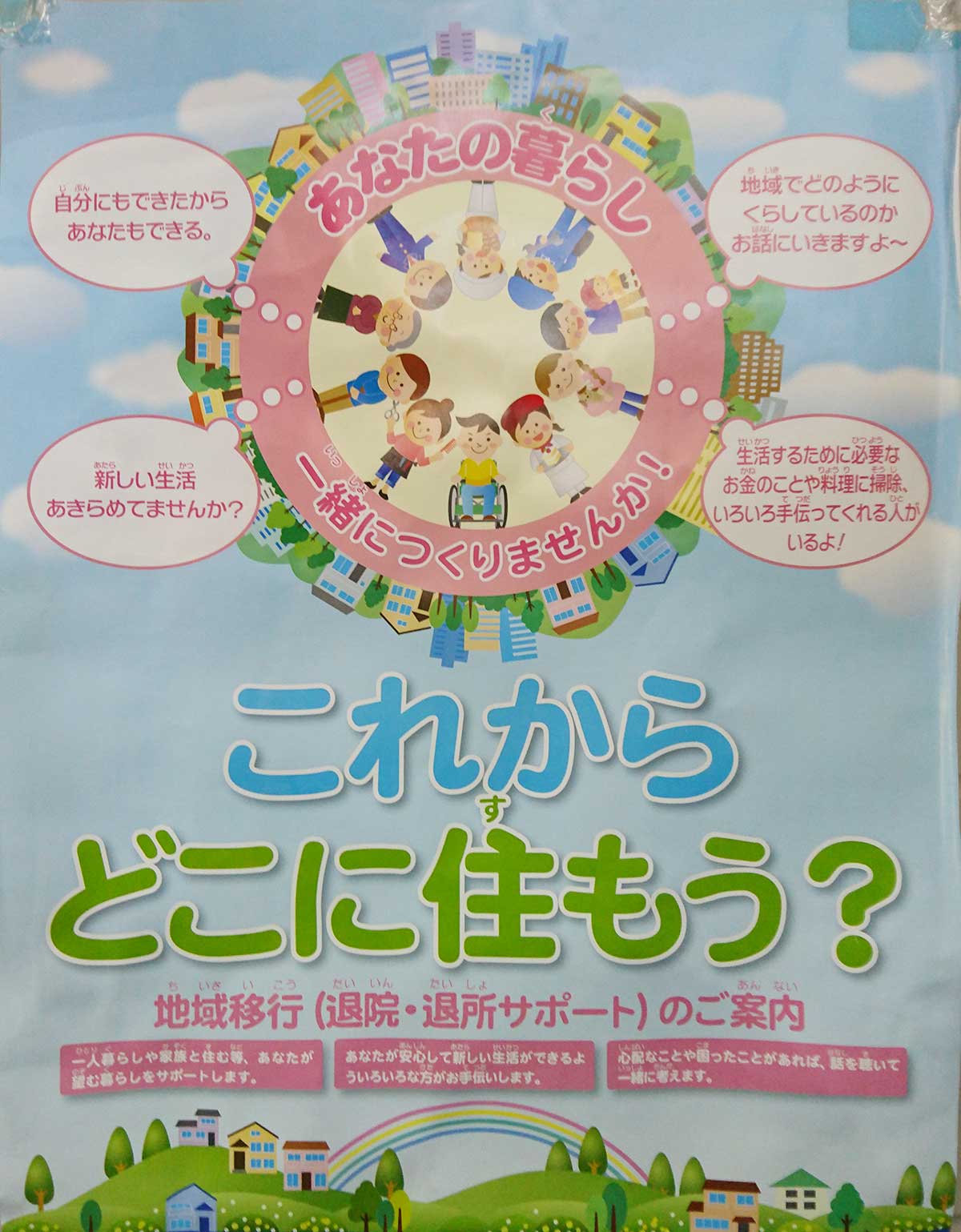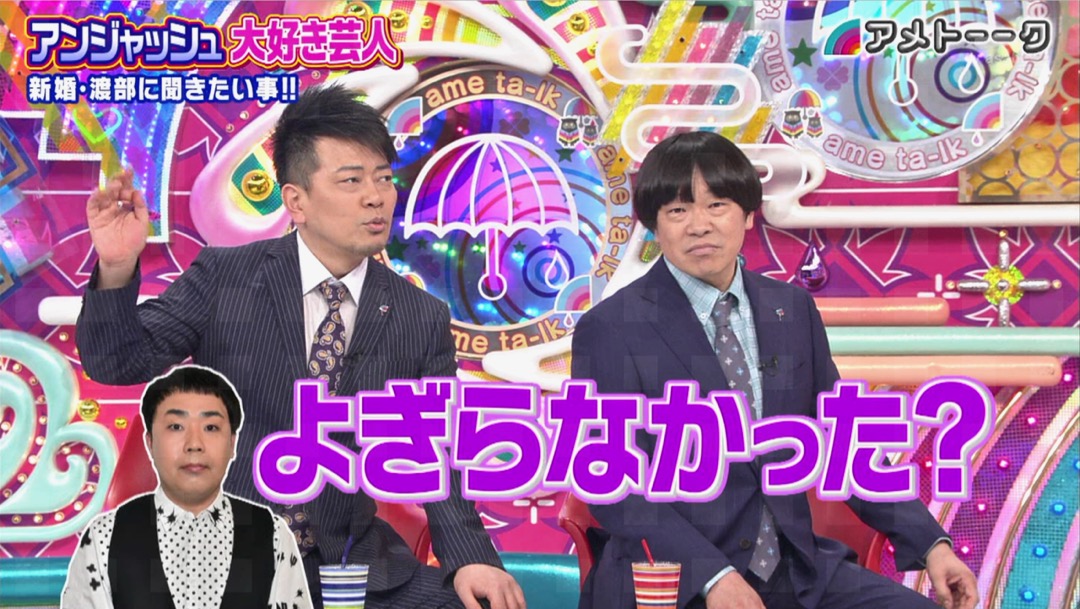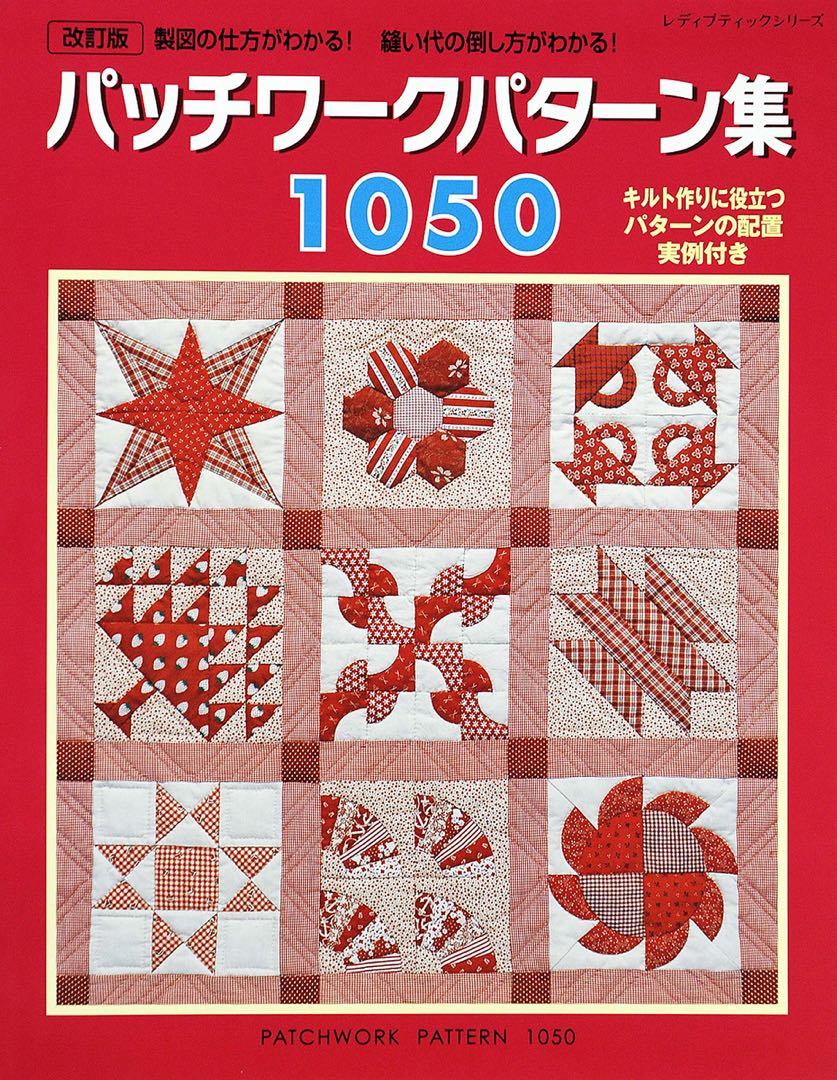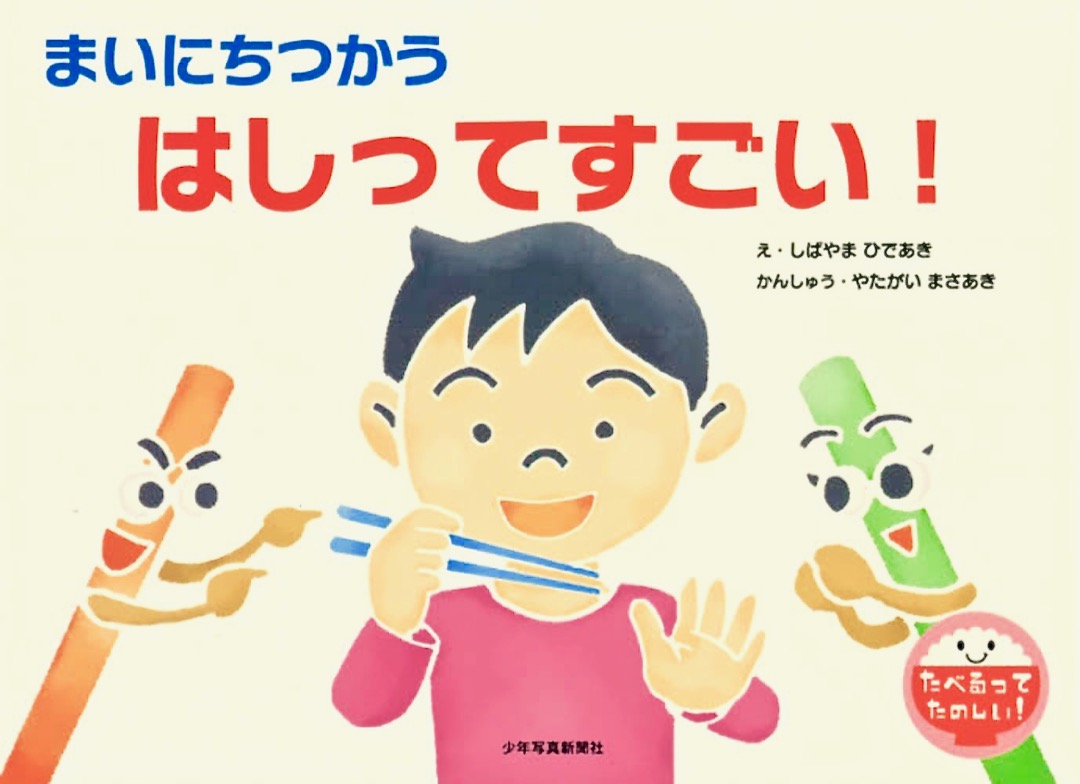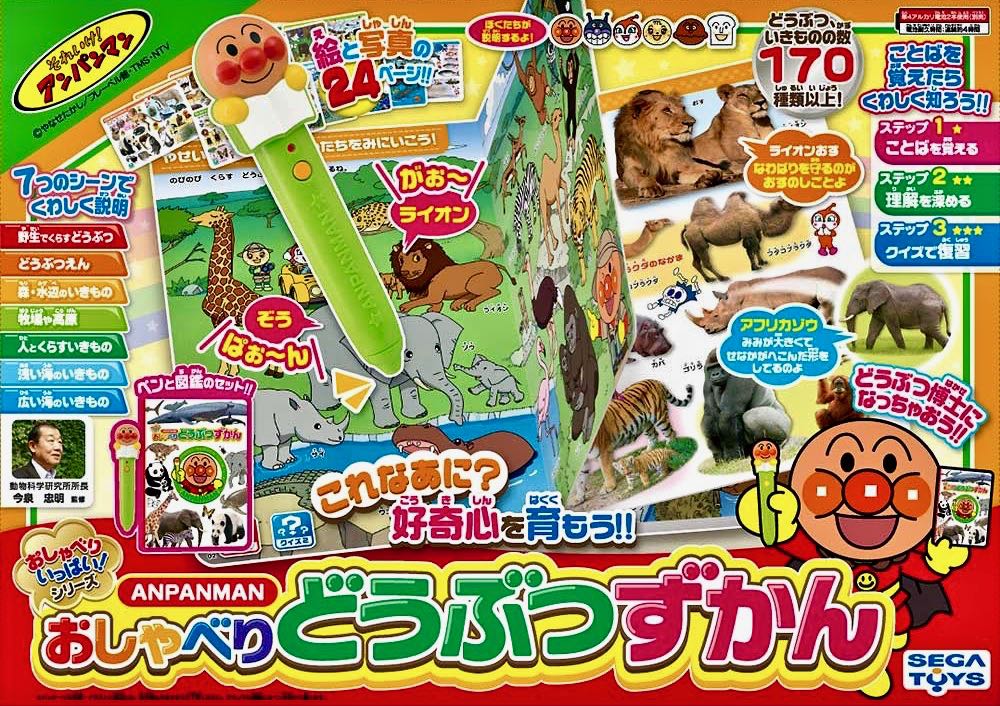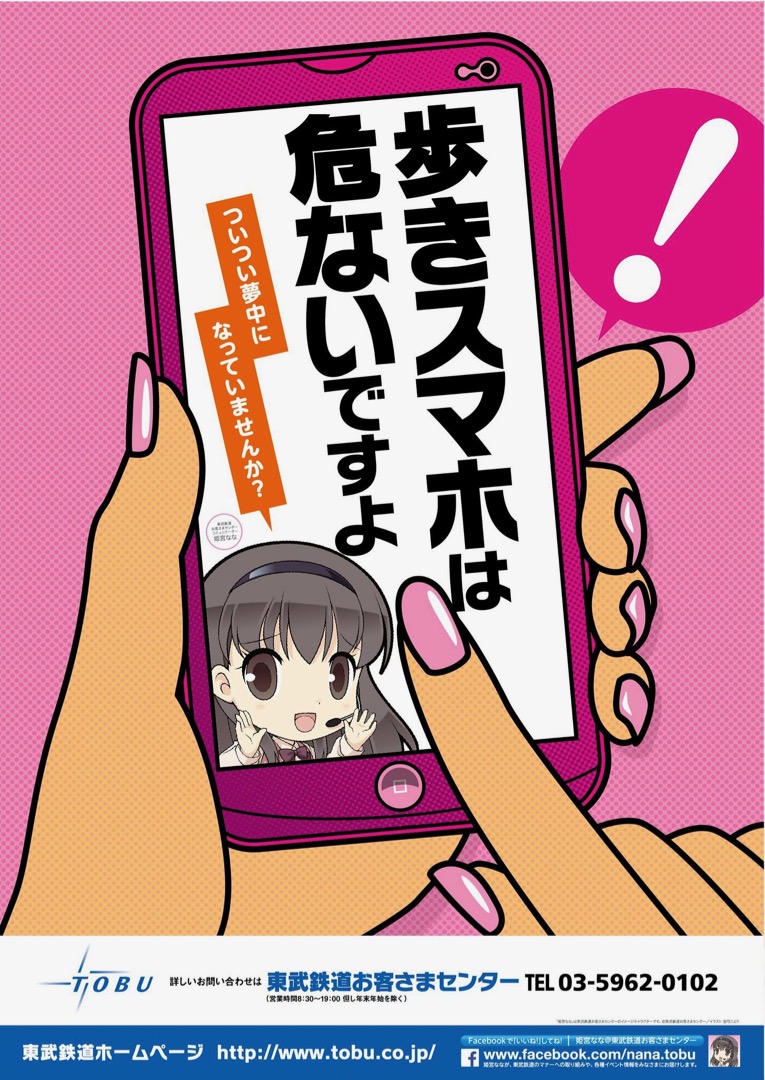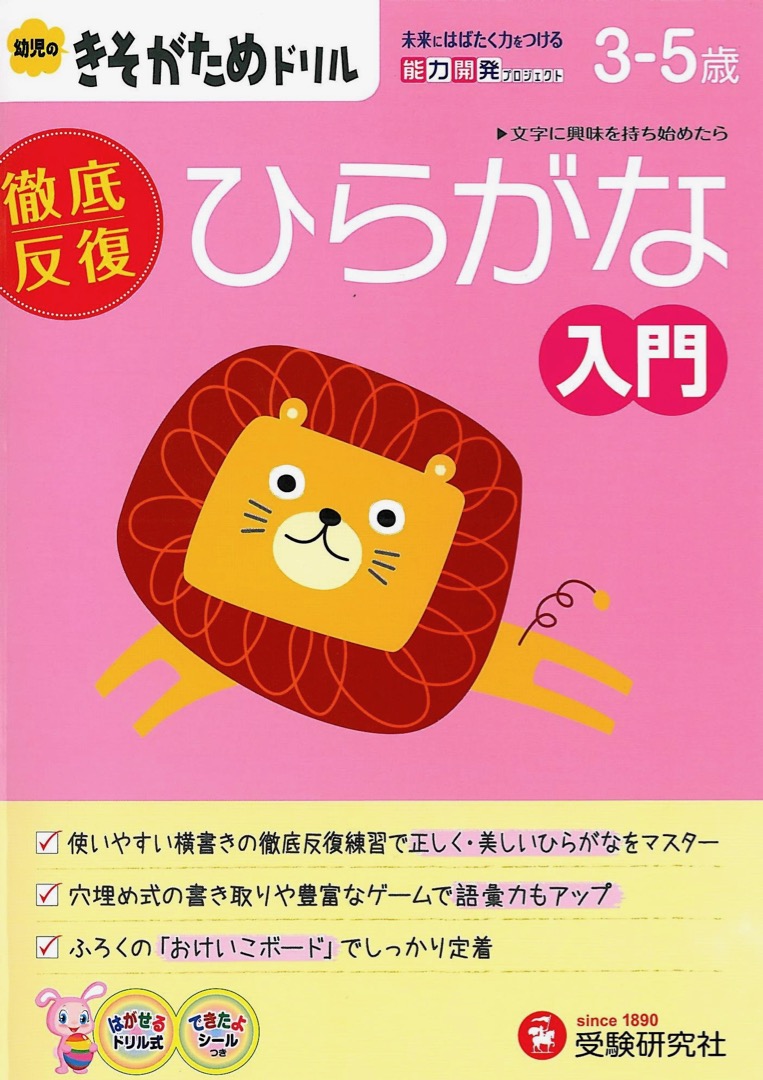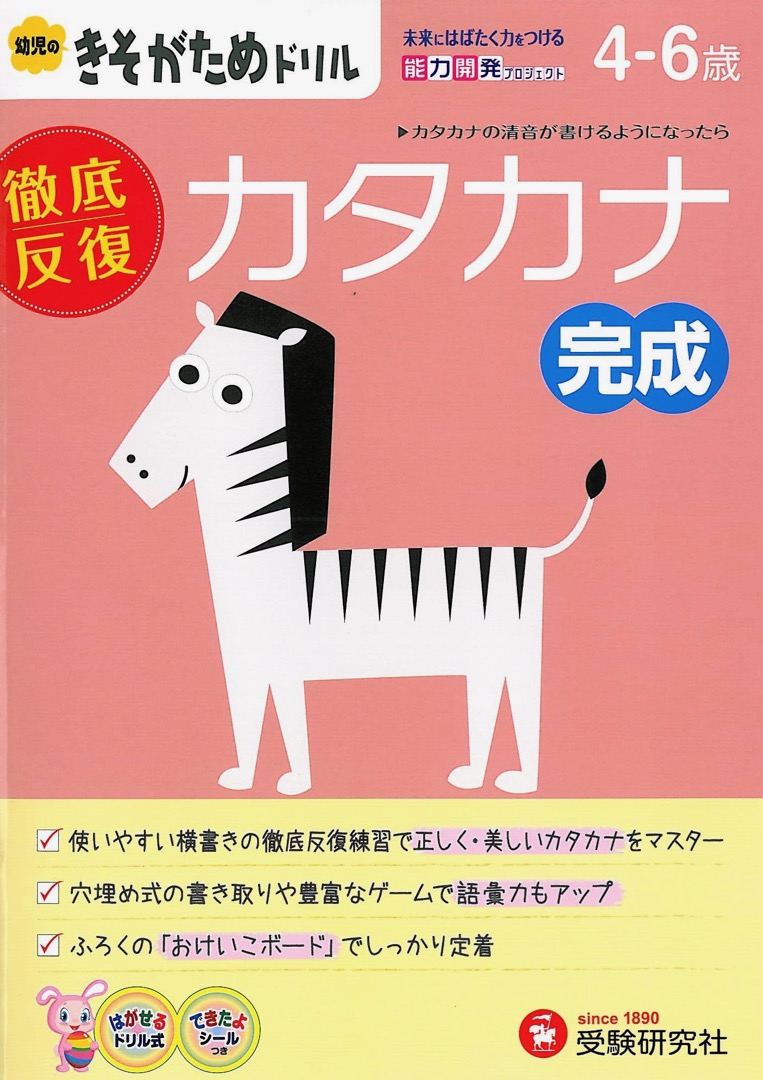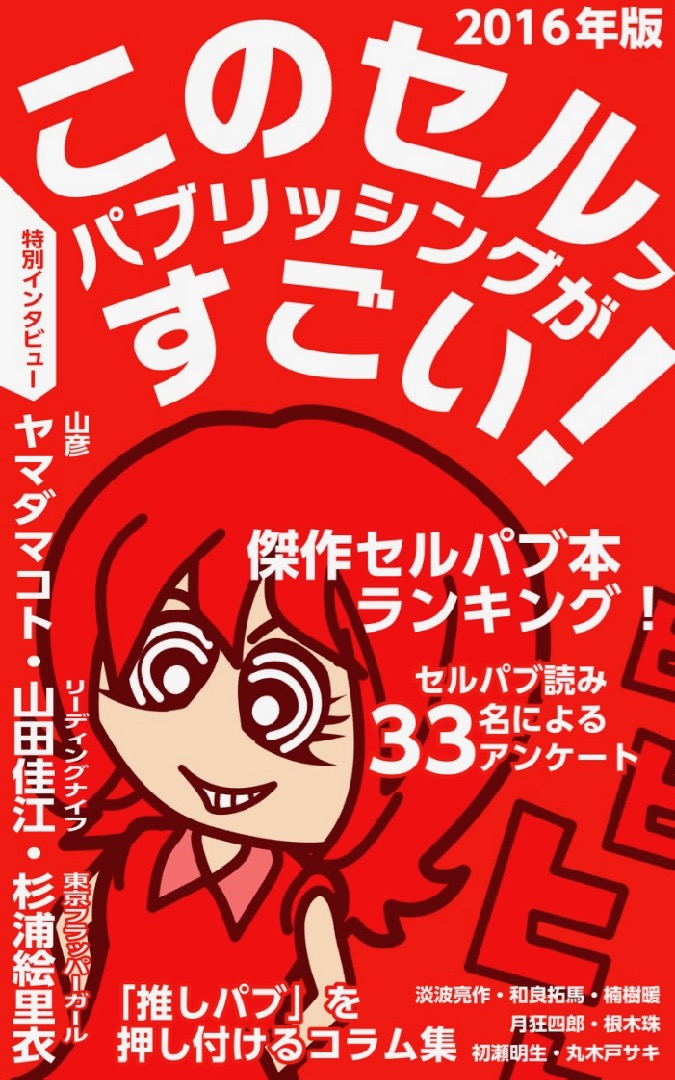
大阪市東住吉区の自転車店の看板です。店名の「サイクルベース」のみです。
この書体のカタカナ文字が気に入ったのでしょうね。
大阪市平野区の、府下最古の朝日新聞販売店の求人募集掲示物です。「シニアスタッフ」での使用です。
リーフレットの写真、文字がわかりにくいのでポスターの方も。
この書体、本当によく使われています〜。
大阪市都市整備局が、6月20日から推薦受付を始めた第32回「ハウジングデザイン賞」の推薦はがき付リーフレットです。
写真は、はがき付リーフレットで、ロゴとして。裏面にも使われています。今回はリーフレットのみですが、ポスターでも使用されています。
ENEOS自体は全国展開ですが、地域のSS(サービスステーション)の新聞折り込みチラシ。「カード入会キャンペーン」のみで使用されています。
大阪市平野区にある総合スポーツクラブの駐車場の看板、広告看板です。
建物本体にも社名がロゴとして使用されていますが、この日は夜間で、建物が撮れる距離になるとストロボが同調しないので撮りませんでした。
小さくてわかりずらいので部分拡大です。
大阪市が、アジア太平洋トレードセンター(ATC)に設置したソフト産業プラザ・イメディオのセミナー案内ニュースです。
「各種サービス利用者募集中」「もうすぐ春です」「イチオシ」「イメディオ」などで使用しています。
テレビ業界で一番使われているタイプラボ書体は、ニタラゴだと思う。
大阪府の府民文化部人権局が発行している人権情報ガイド誌第32号です。
「ゆまにて」って、人類・人間性・人間の本性(en:Humanity、en:Human nature)に相当するフランス語…なんですね。